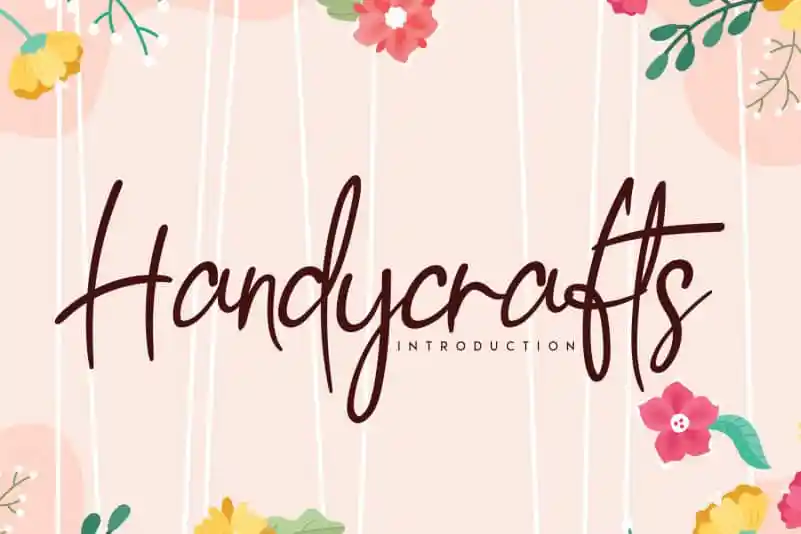
Handycrafts Handwritten Font – Download Grátis
A fonte ‘Handycrafts Handwritten Font’ foi projetada especialmente para pessoas que buscam uma experiência única ao criar produtos de manufatura artesanal. Ela é perfeita para designers e criativos que desejam adicionar um toque único a seus designs digitais, oferecendo uma escrita legível mas sofisticada que não se tornará monótona por usar repetidamente. Com sua aparência natural e envolvente, esta fonte irá certamente deixar seu trabalho de manufatura artesanal se destacar. A cada letra, o usuário pode experimentar a diversidade da escrita humana, do familiar aos mais elaborados, criando um visual que é tanto pessoal quanto inspirador. Essa fonte traz uma sensação de autenticidade e personalização para seu projeto, tornando-o único e memorável. Seja você um designer gráfico, um artesão ou alguém simplesmente buscando adicionar uma pegada mais humana a seus projetos digitais, ‘Handycrafts Handwritten Font’ é sua fonte perfeita.